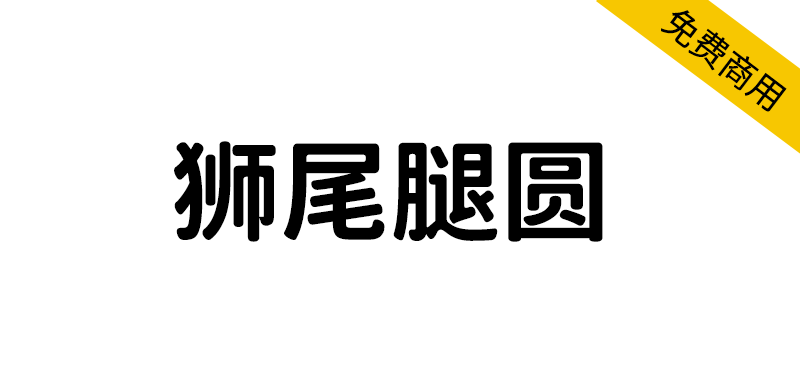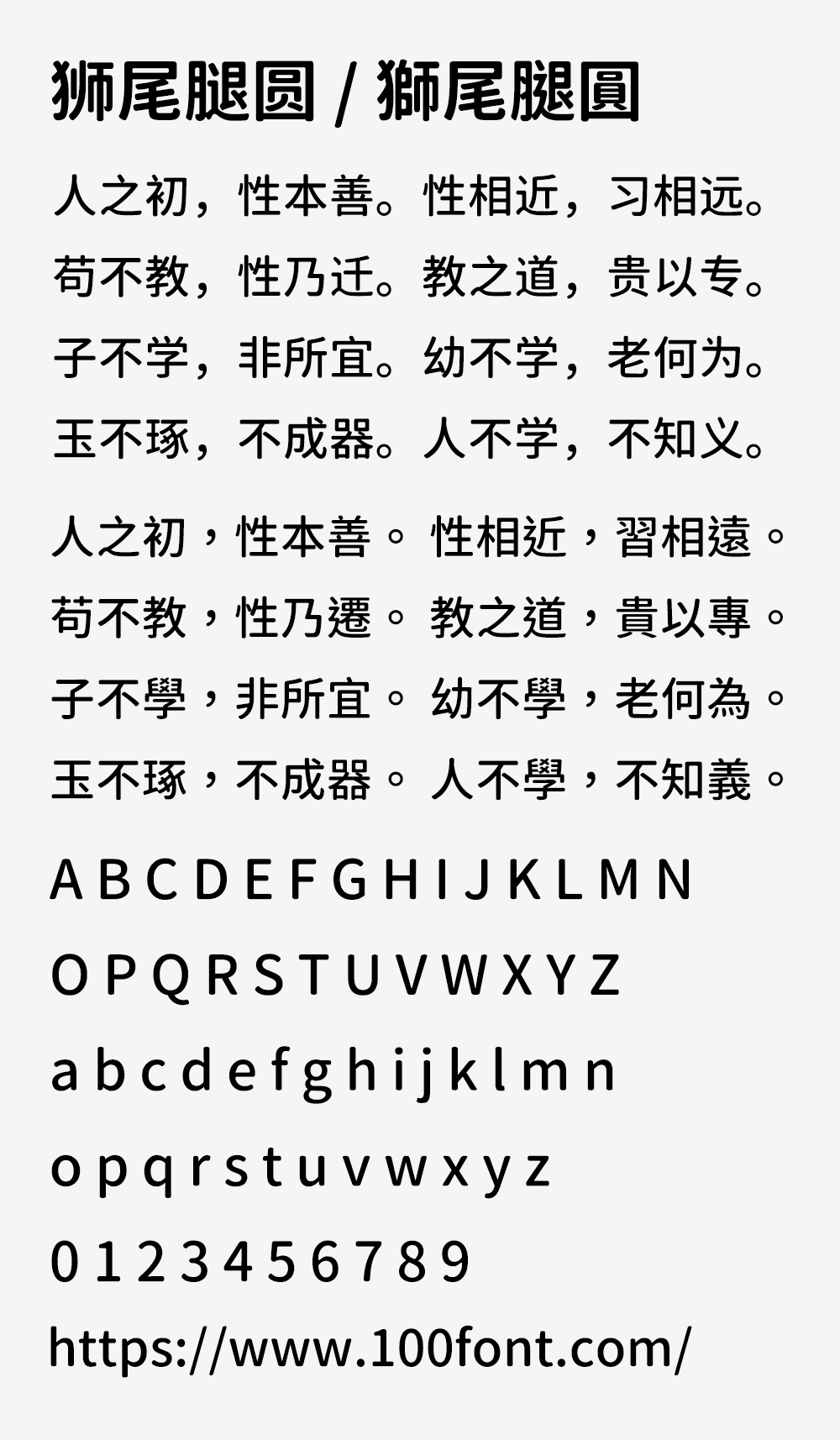
狮尾腿圆基于思源黑体变圆改造,和狮尾圆体的差别在有长腿,更加简明现代化的字体。和思源黑体一样,有7种字重,支持简体中文、繁体中文、韩文与日文,可以免费商用,欢迎大家自由应用、自由优化、自由改作!
狮尾腿圆和「狮尾圆体」差别在有没有拔脚,「拔脚」就是会有较少的笔画,例如移除「口」字的左右下角会多出的短线条。有拔脚的字会较圆,但是会造成有些字因直接去掉腿后左右不平衡、左右不对衬的「悬空」问题。改使用「腿」系列字体就不会有这个问题。